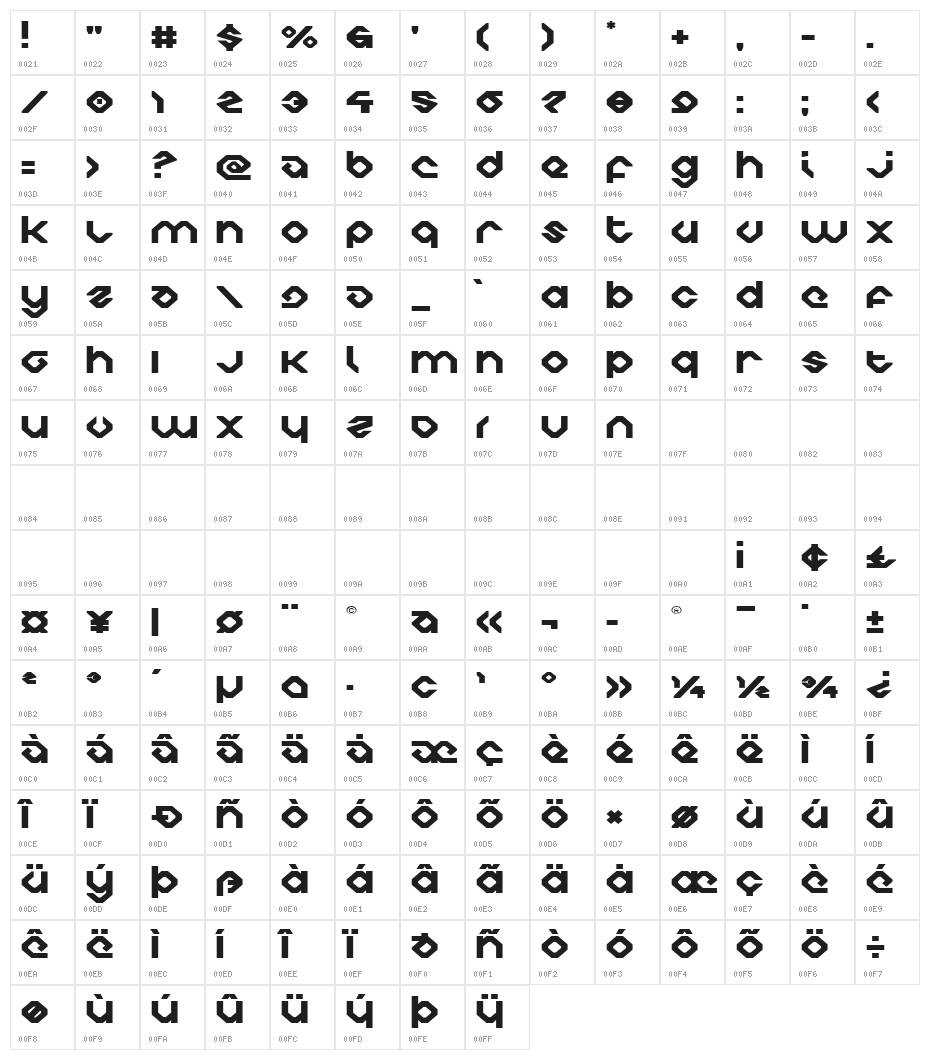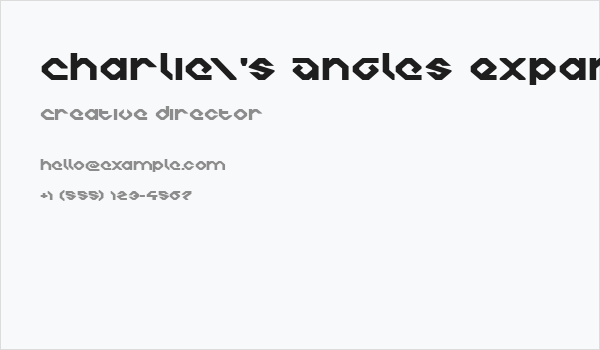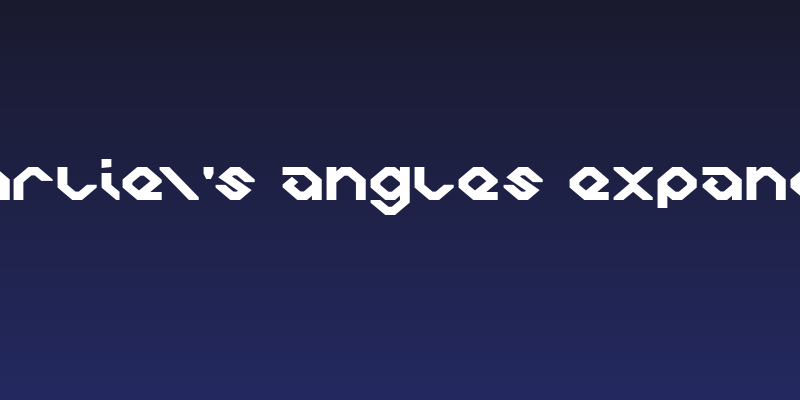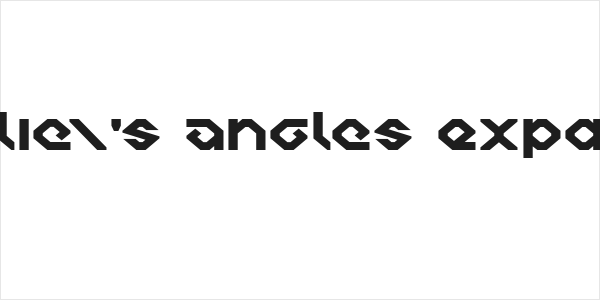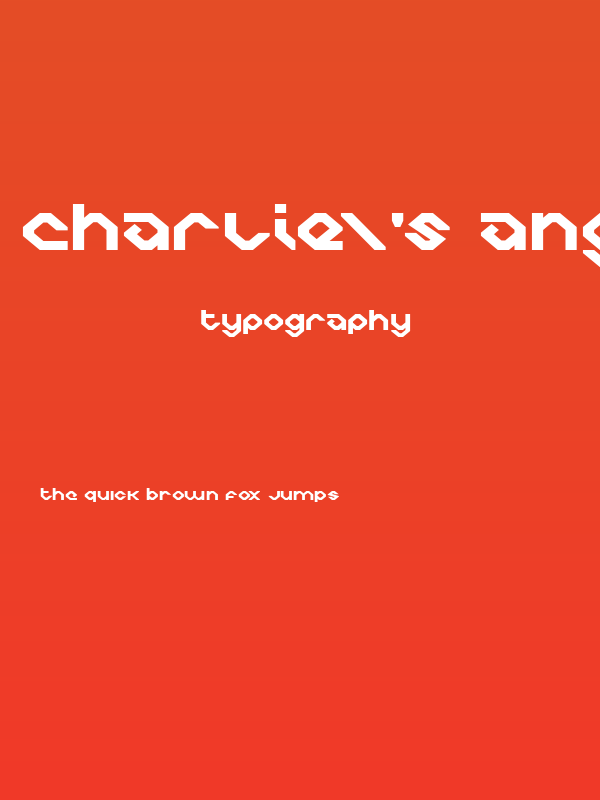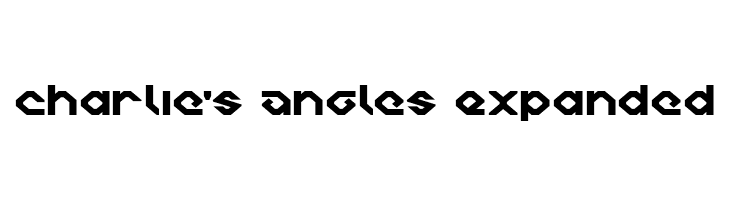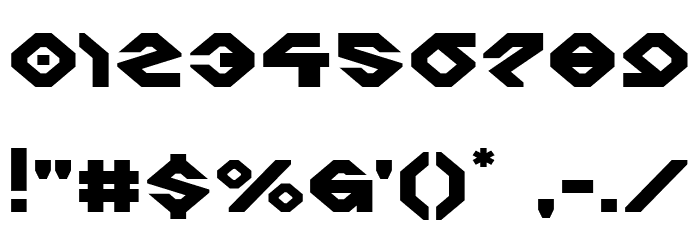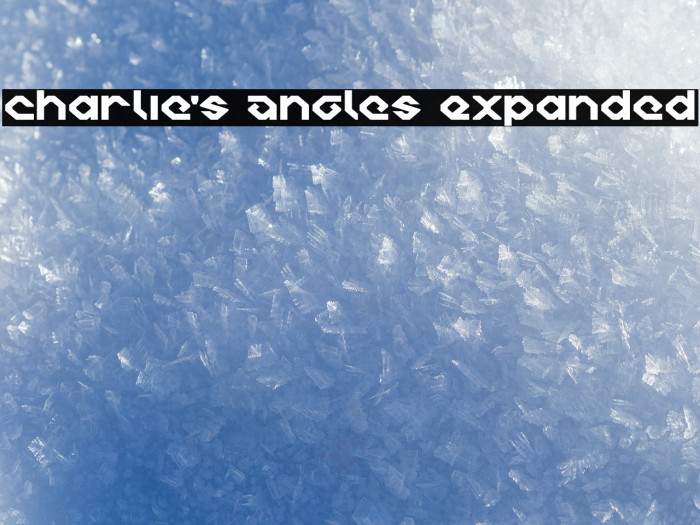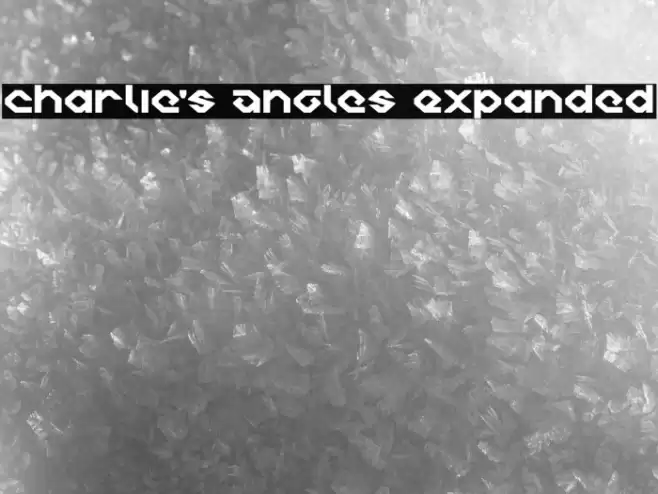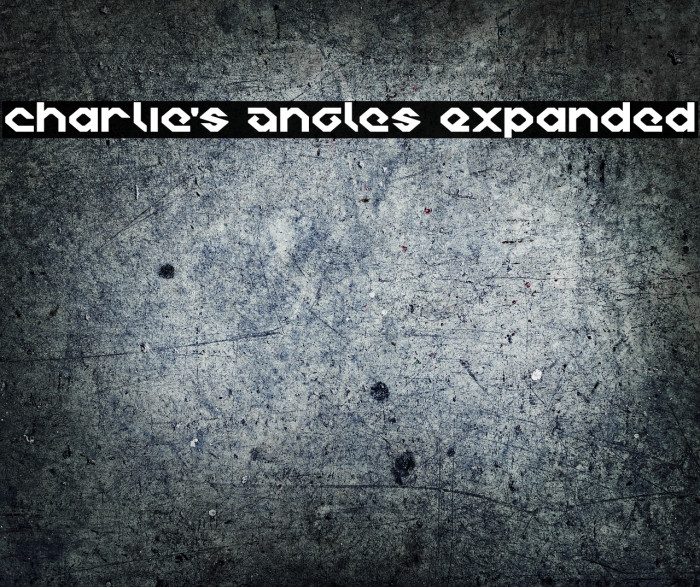
Charlie's Angles Expanded Font
| الفئات | Futuristic |
| العرض | Expanded |
| النمط العام | Futuristic |
| حالة الاستخدام | Logos, Headlines, Posters |
| مشاريع مقترحة | Ideal for sci-fi themed projects, digital artwork, video game design, and modern branding. |